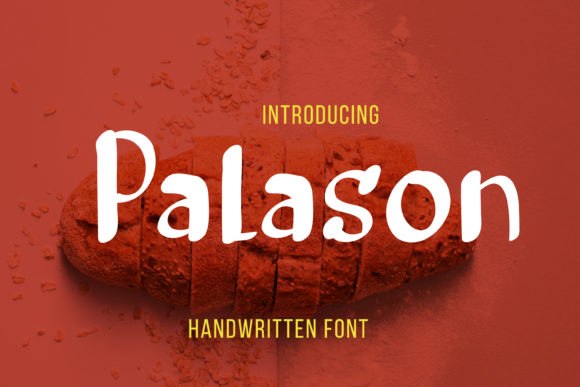
Паласон - игривый и смелый рукописный шрифт.
Его изысканный и модный стиль делает этот шрифт идеальным выбором для широкого спектра дизайнов.
Используйте этот шрифт для ваших дизайнов и изучите его бесконечные возможности.